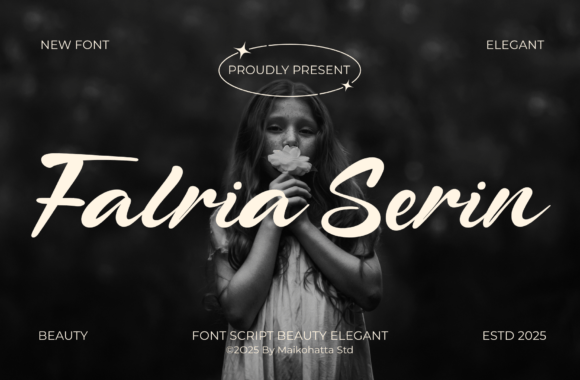
Falria Serin
適切なデザイン要素を見つけるのは難しい場合がありますが、Falria Serinは作品を即座に引き立てる優れたコレクションを提供します。
精密に作られたFalria Serinは、クリーンなベクター、滑らかなタイポグラフィ、そして安心のための商用ライセンスを提供します。
POD(オンデマンド印刷)製品、結婚式の招待状、またはソーシャルメディアのグラフィックを作成している場合でも、Falria Serinは理想的です。